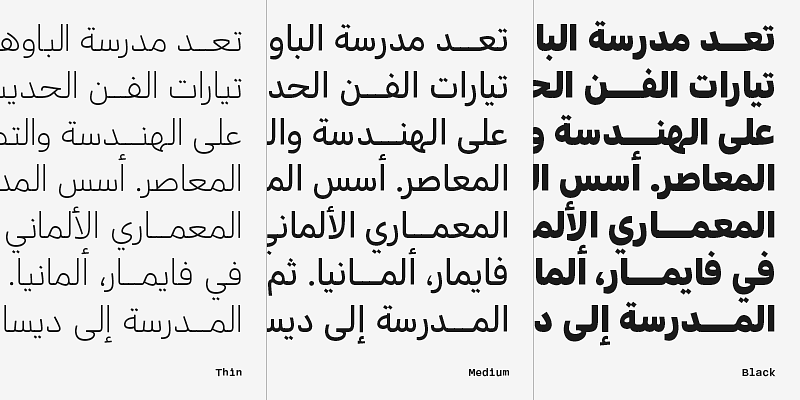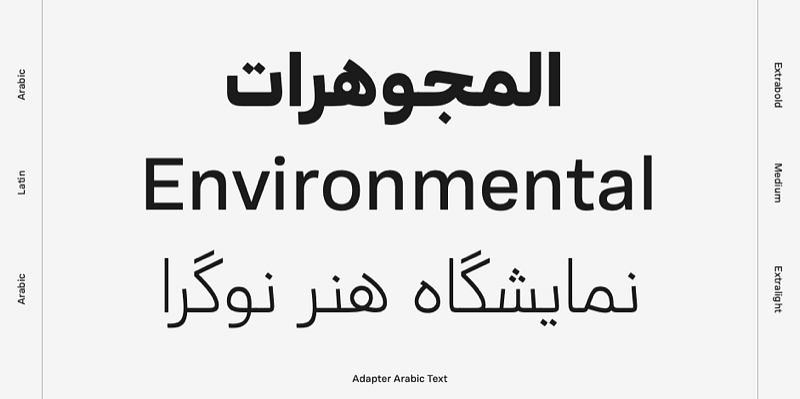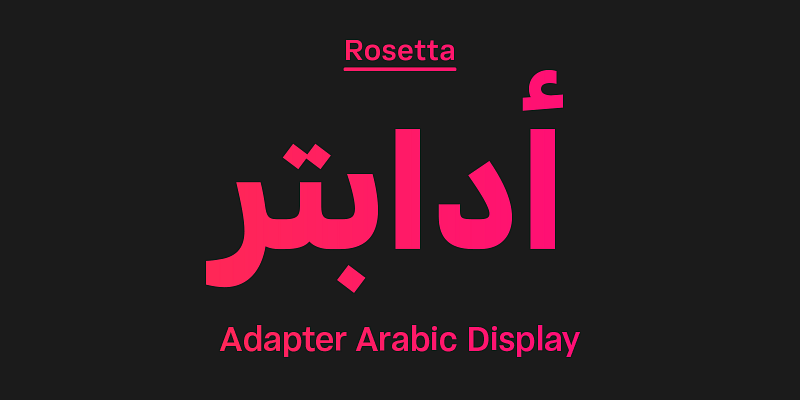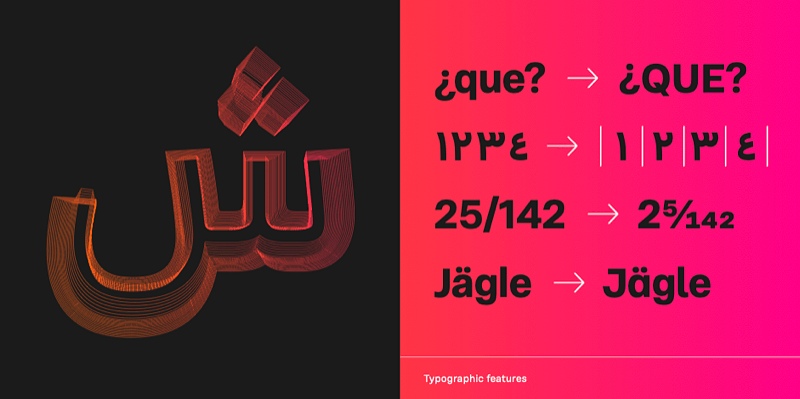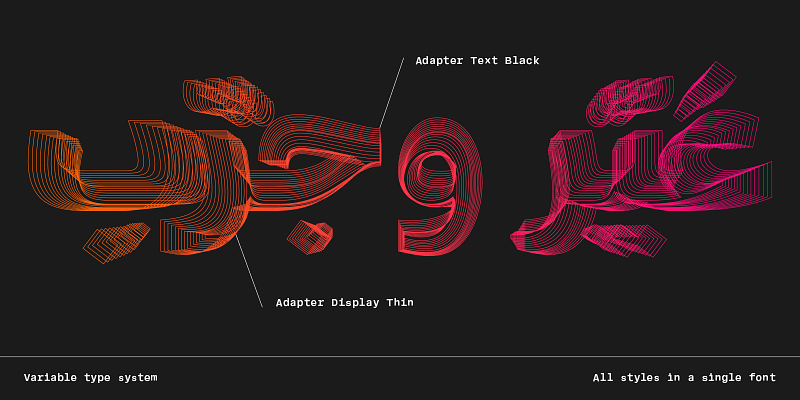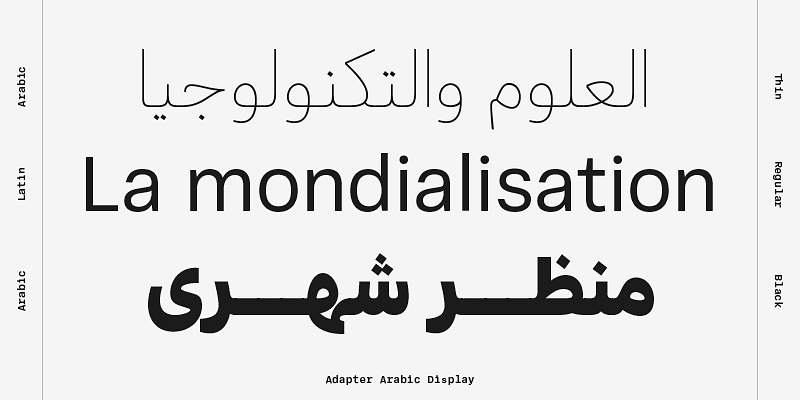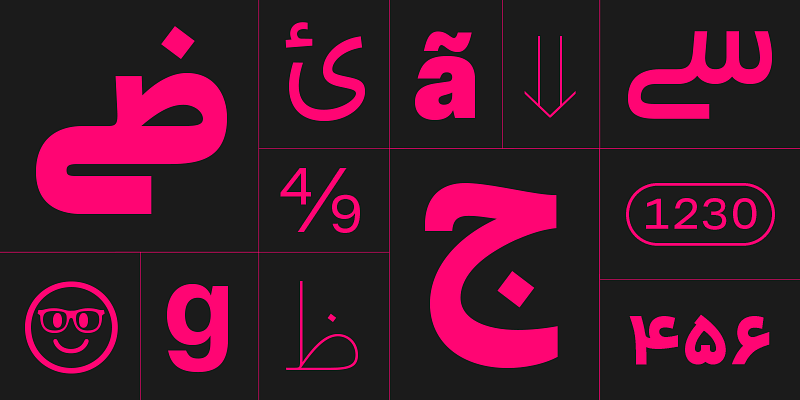
Eine universelle monolineare Schrift mit aktueller Ästhetik. Die beiden größenspezifischen Varianten Text und Display sind in ein Schriftensystem eingebunden, das eine Vielzahl von Schriftstärken und Kursive mit einheitlicher Breite in einer variablen Schrift vereint.